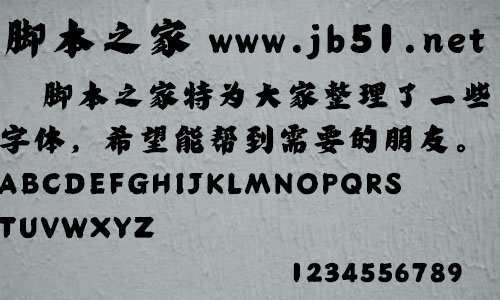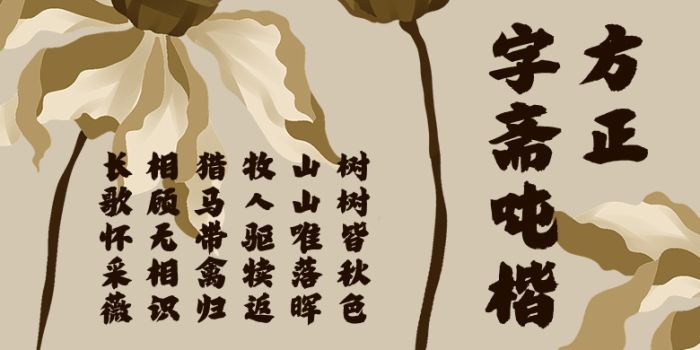
方正字齋噸楷由方正字庫劉漢旭設(shè)計(jì)師出品的藝術(shù)字體,該字筆觸粗實(shí),字形端正,適合應(yīng)用于藝術(shù)設(shè)計(jì)、平面宣傳設(shè)計(jì)、網(wǎng)頁設(shè)計(jì),書法等領(lǐng)域。
字體介紹
《方正字齋噸楷》是一款適合表達(dá)人文與力量相關(guān)屬性的字體,其字體不但醒目,而且還有分量,可以給人新的視覺感知,喚起新的潮銳。這款字是立足于力量的創(chuàng)意書寫,它與生俱來的視覺沖擊力使其尤其適合作為標(biāo)題字。 字體是有容顏的,有的長(zhǎng)著一副大眾臉,有的讓人過目不忘,看似普通的字體,卻暗藏著不為人知的能量。字體的容顏即字體的神態(tài)、神情、表情,外觀相貌。能從表象、現(xiàn)象透出來的本質(zhì)、實(shí)質(zhì)、特質(zhì)才是產(chǎn)品本身所想要訴求的。在字體中由形推神到質(zhì),通過設(shè)計(jì)是可以倒推出來。對(duì)字體進(jìn)行察言觀色,不失為一個(gè)好方法